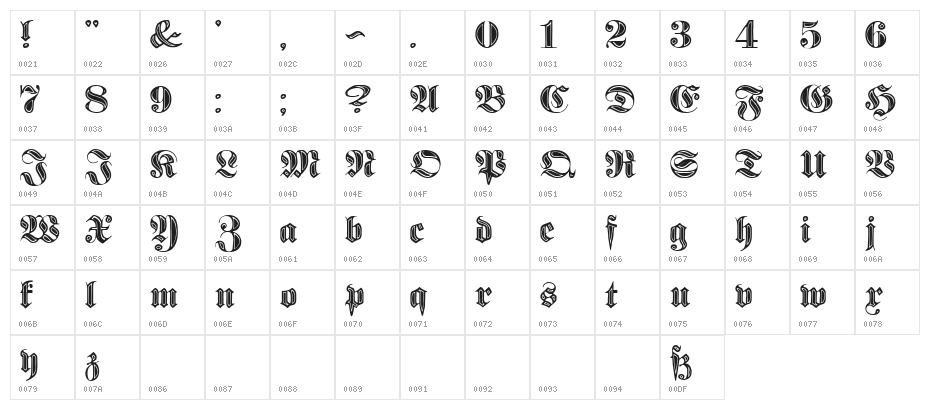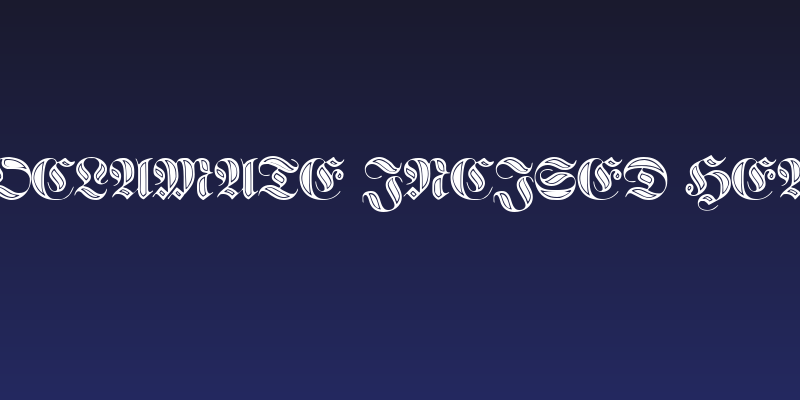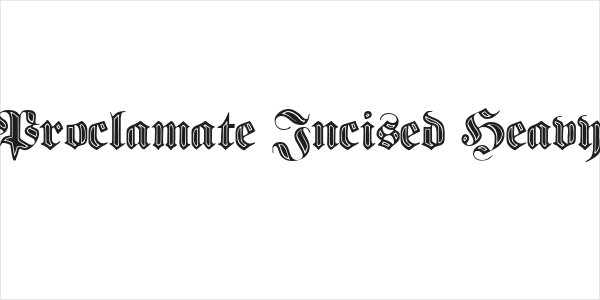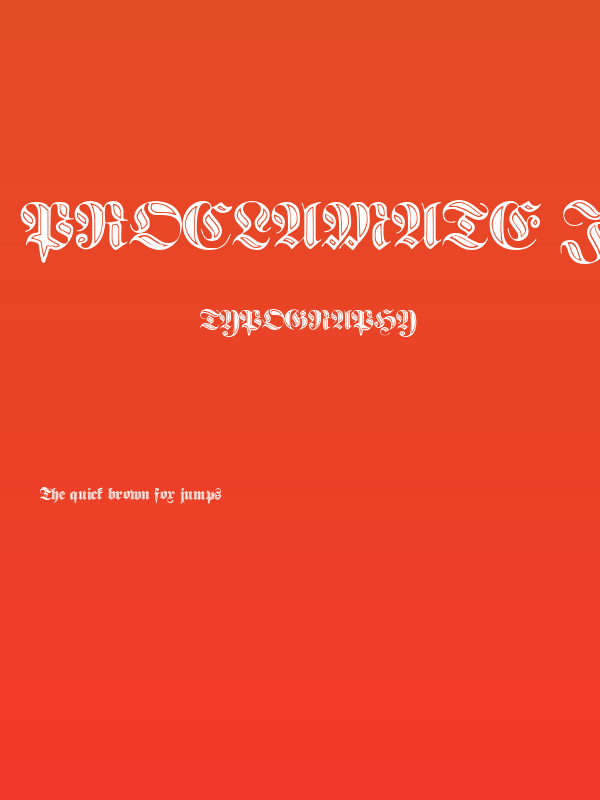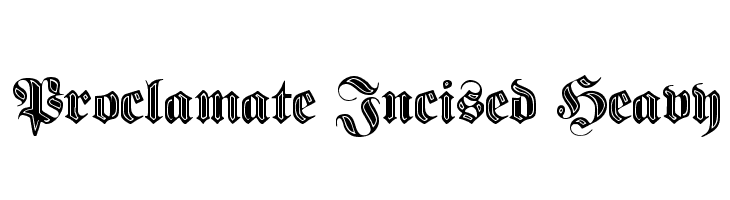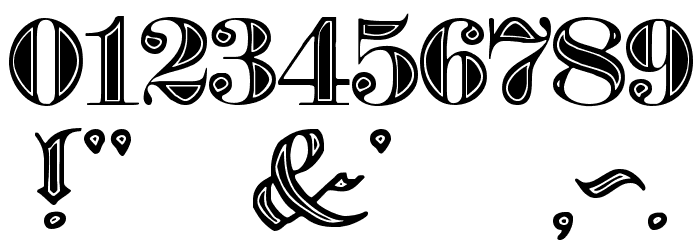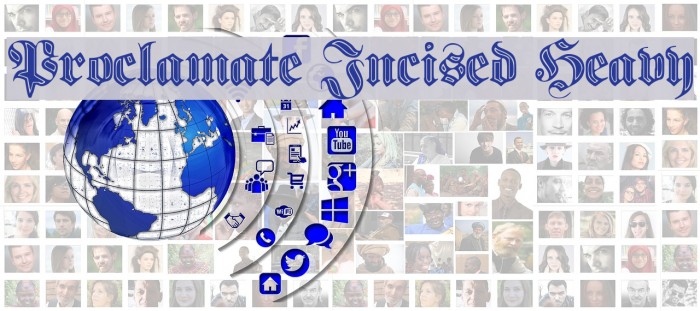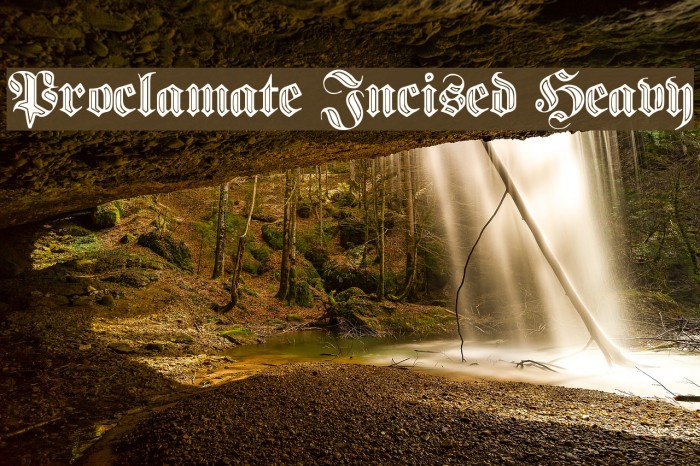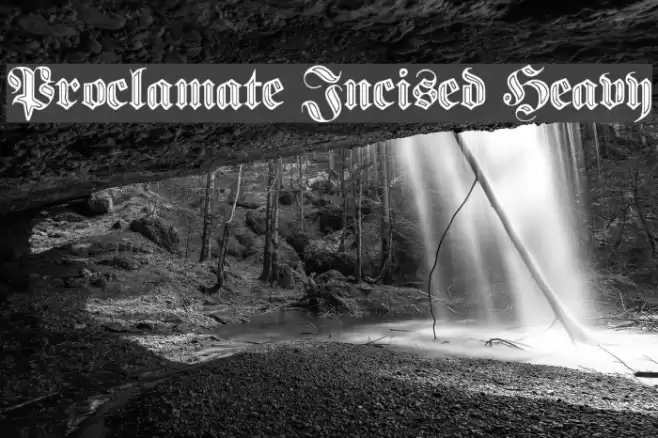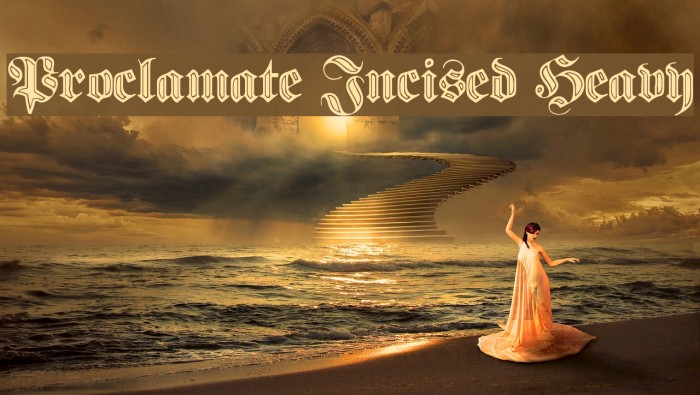
Proclamate Incised Heavy Font
✎ Gothic
| Kategorien | Gothic |
| Gesamtstil | Vintage |
| Anwendungsfall | Headlines, Logos, Decorative text |
| Vorgeschlagene Projekte | Suitable for certificates, formal invitations, branding for luxury products, or any project needing a touch of historical elegance. |